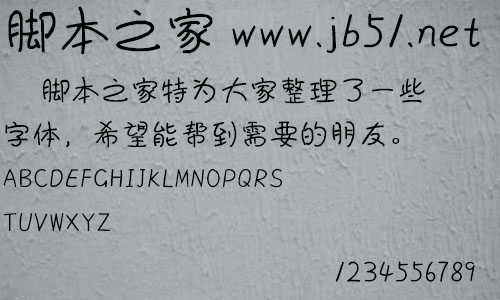
以青春為名字體是一款中文藝術(shù)字體,這款字體字形圓潤(rùn),看上去十分的可愛(ài),適合應(yīng)用于藝術(shù)設(shè)計(jì)、平面宣傳設(shè)計(jì)、網(wǎng)頁(yè)設(shè)計(jì),書法字帖等領(lǐng)域。歡迎需要的朋友前來(lái)本站下載使用。